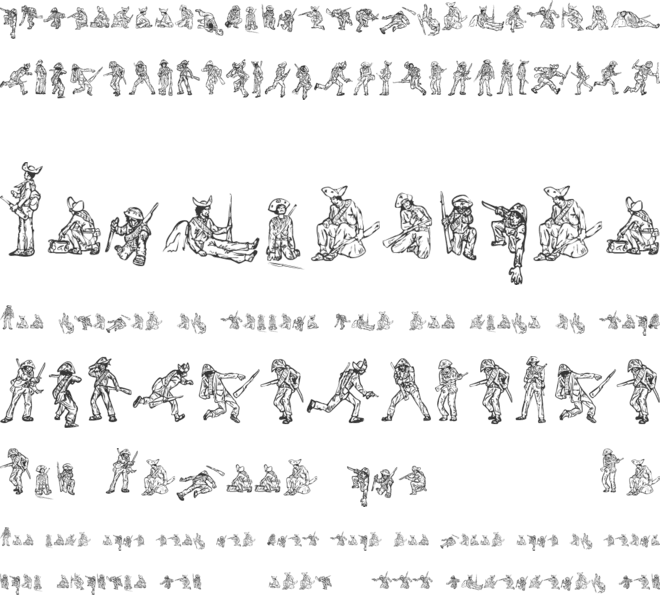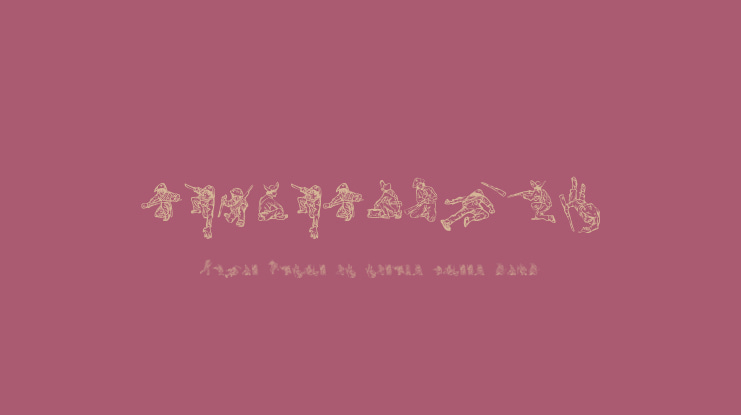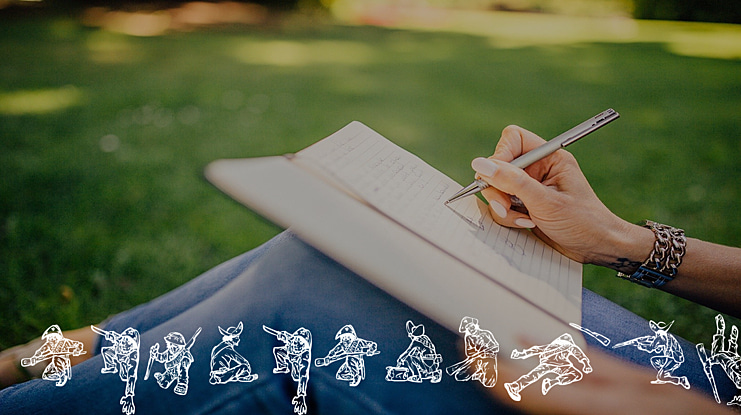
cangaceiros Font
O dingbat cangaceiro são ilustrações de cangaceiros, a maioria representado em movimento de luta. Segue a lógica de CA são personagens eretos e os caracteres Cb os personagens agachados ou deitados.